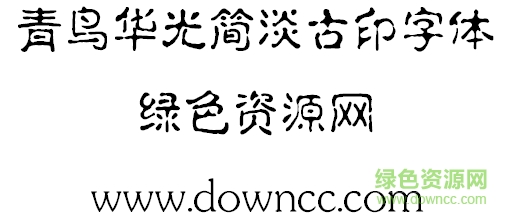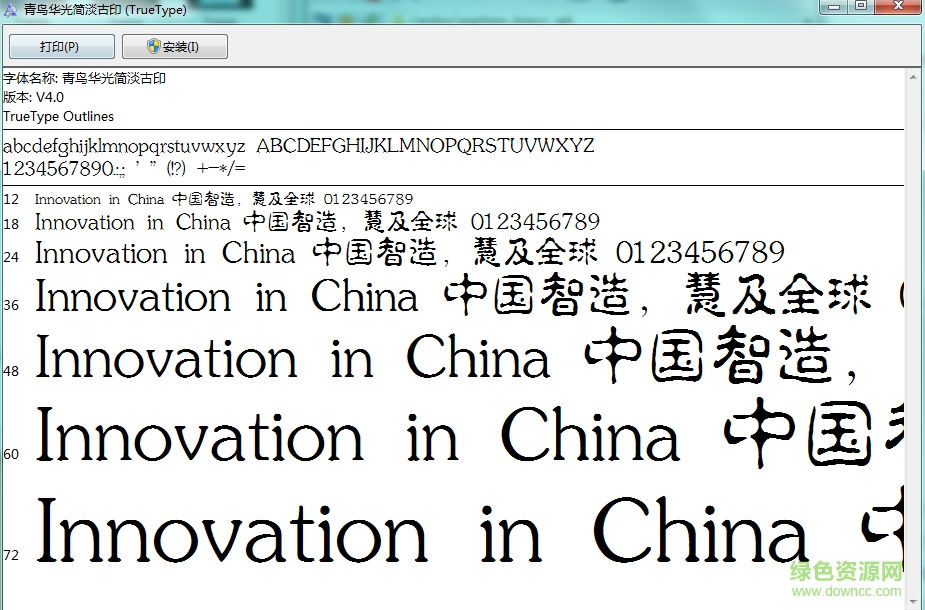
青鳥華光簡(jiǎn)淡古印是一款中文簡(jiǎn)體輸入的古印字體,有著柔和娟秀的筆觸,淡淡的痕跡如古書刻印,彰顯古風(fēng)飄逸和灑脫之感,喜歡的朋友來(lái)綠色資源網(wǎng)即可下載哦!
青鳥華光簡(jiǎn)淡古印是青鳥華光推出的古法印刷的藝術(shù)字體,共有8774個(gè)字符。
古印和淡古大同小異,屬于仿漢印章剝蝕效果的今文字。其點(diǎn)畫有斷有連,似斷似連,結(jié)構(gòu)造型似在楷、隸之間。
其藝術(shù)風(fēng)格:干枯、老辣、古樸、悠久。
書法體體系的主要藝術(shù)特征是生動(dòng)活潑,造型美麗,藝術(shù)風(fēng)格高雅。相互比較而言:印篆古雅,隸書質(zhì)樸,魏碑骨力,楷書秀麗,行書飄逸,古印殘舊。